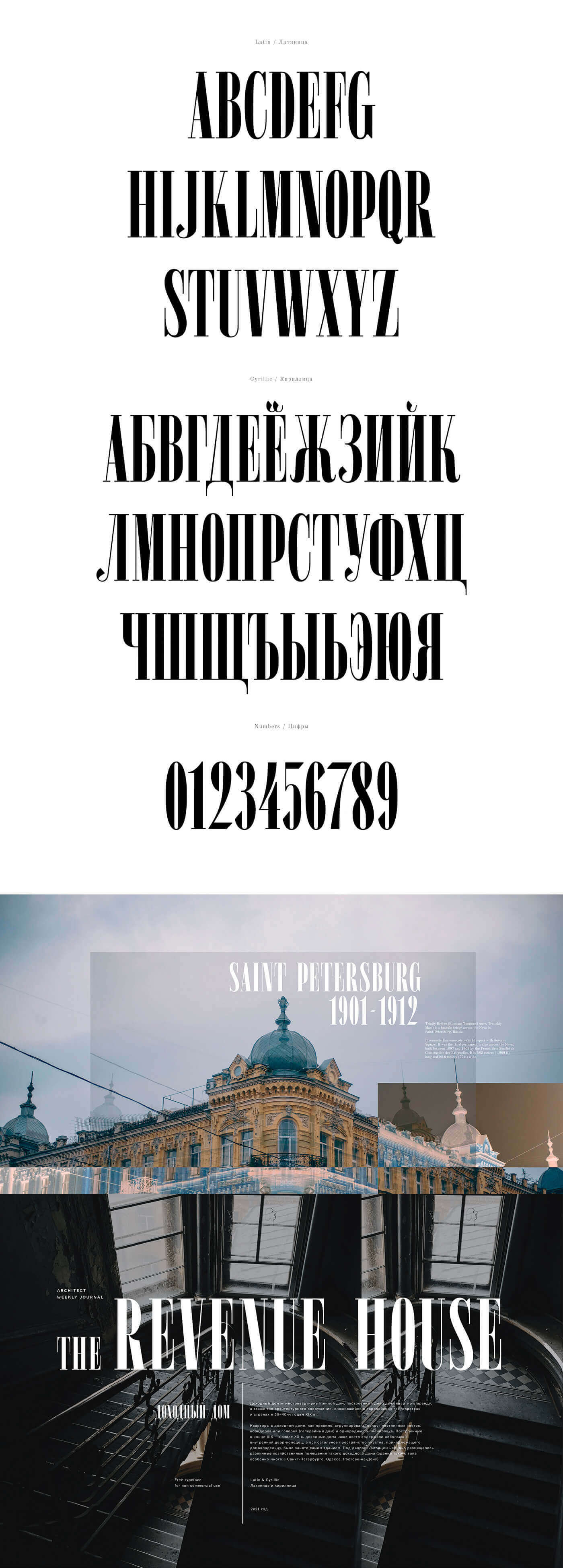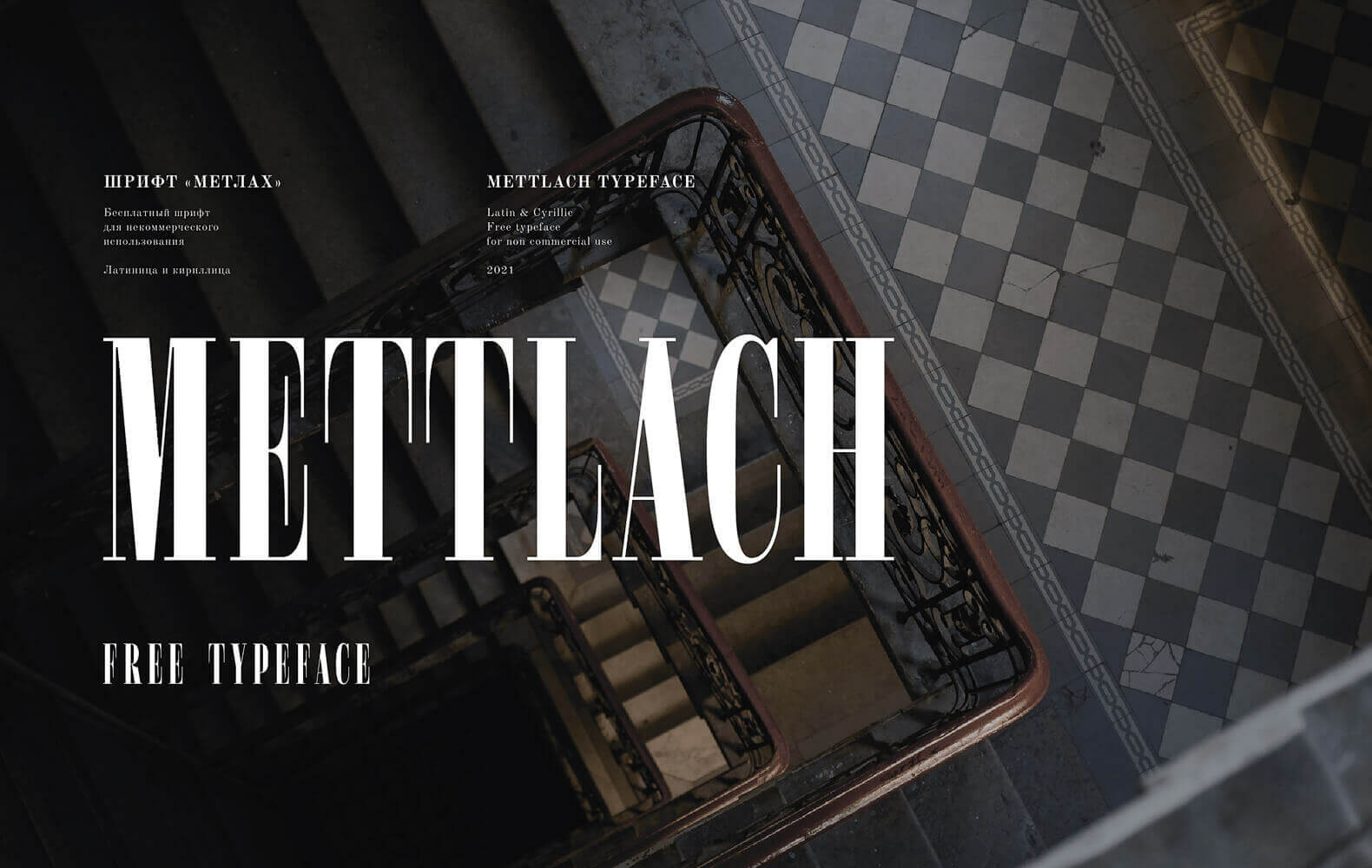
Шрифт Метлах/Mettlach (Кириллица/Латиница)
«Метлах» подражает шрифтам конца XIX — начала XX века., но имеет современное происхождение. Это высококонтрастный и зауженный шрифт, который хорошо смотрится в крупном кегле на логотипах и заголовках.
Спасибо! Такого шрифта у меня ещё не было: цифры здесь красивые (если их ужать по вертикали в районе 60-90%, то, кроме "4", должно что-то интересное в комбинаторике получиться...) - заберу в коллекцию.